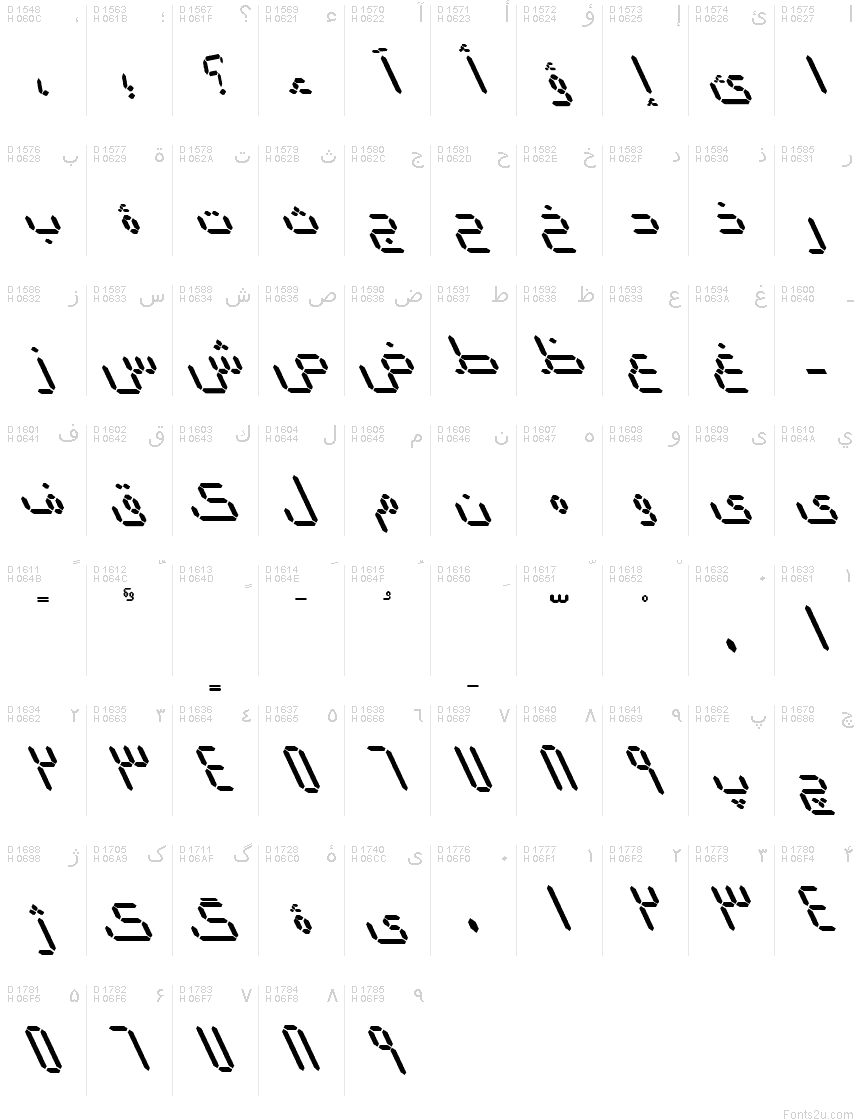
B Elm Italic di Borna Rayaneh è un font arabo gratuito per display digitale, formato da tratti inclinati e segmentati che ricordano più le cifre a LED che le lettere convenzionali. Questa costruzione ripetitiva e frammentata conferisce al design un ritmo codificato e meccanico, rendendolo perfetto per segnali, contatori e grafica a schermo piuttosto che per testi neutri.
Locandine di eventi, interfacce di gioco, intestazioni di app, copertine musicali e branding tecnologico: tutti possono sfruttare questo impulso angolare. Questo font gratuito dà il meglio di sé quando la scritta deve apparire scattante e sintetica. È particolarmente convincente nei titoli brevi, nelle schermate di apertura e nei loghi, dove le forme segmentate rimangono nitide e ben leggibili.